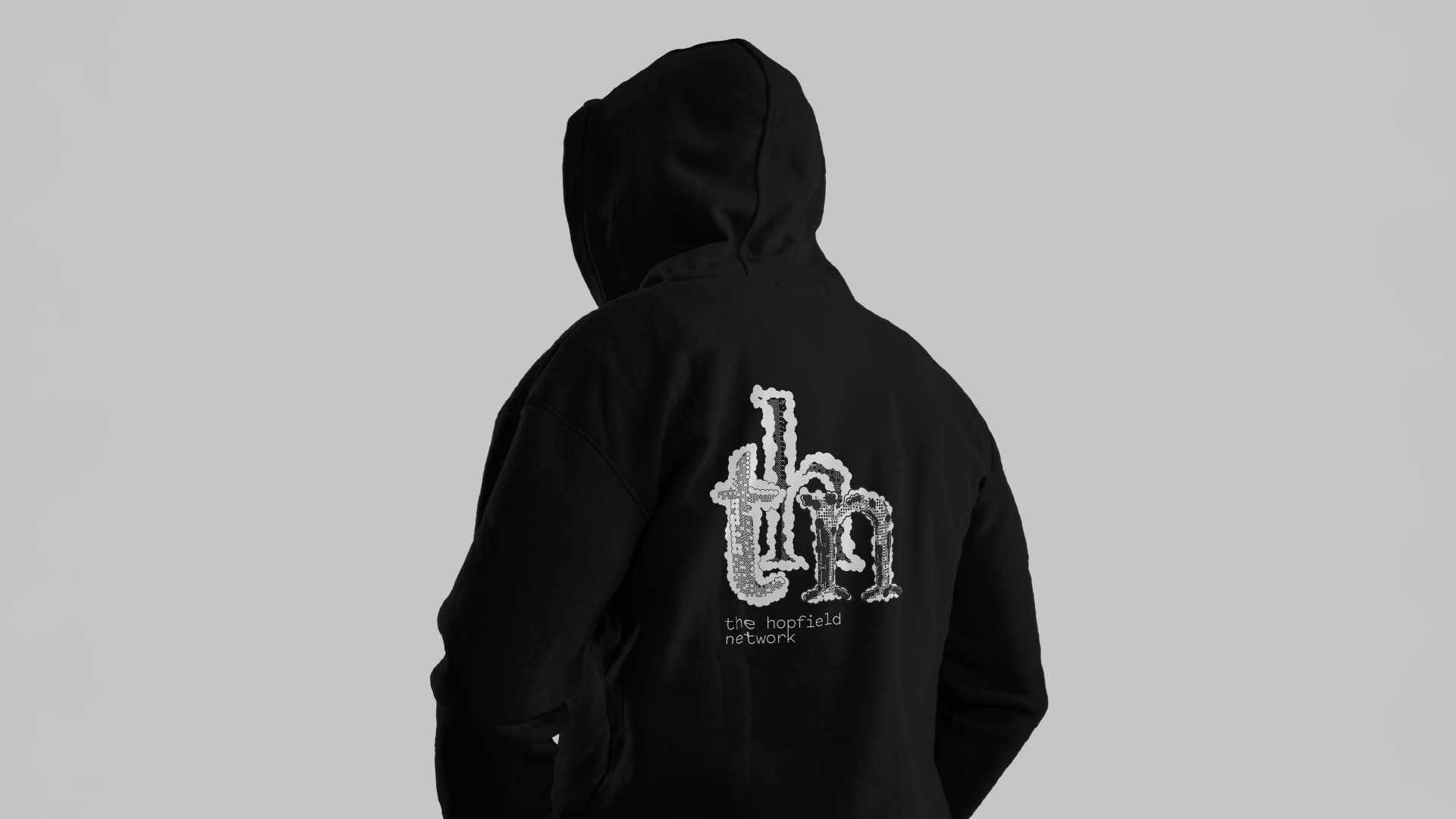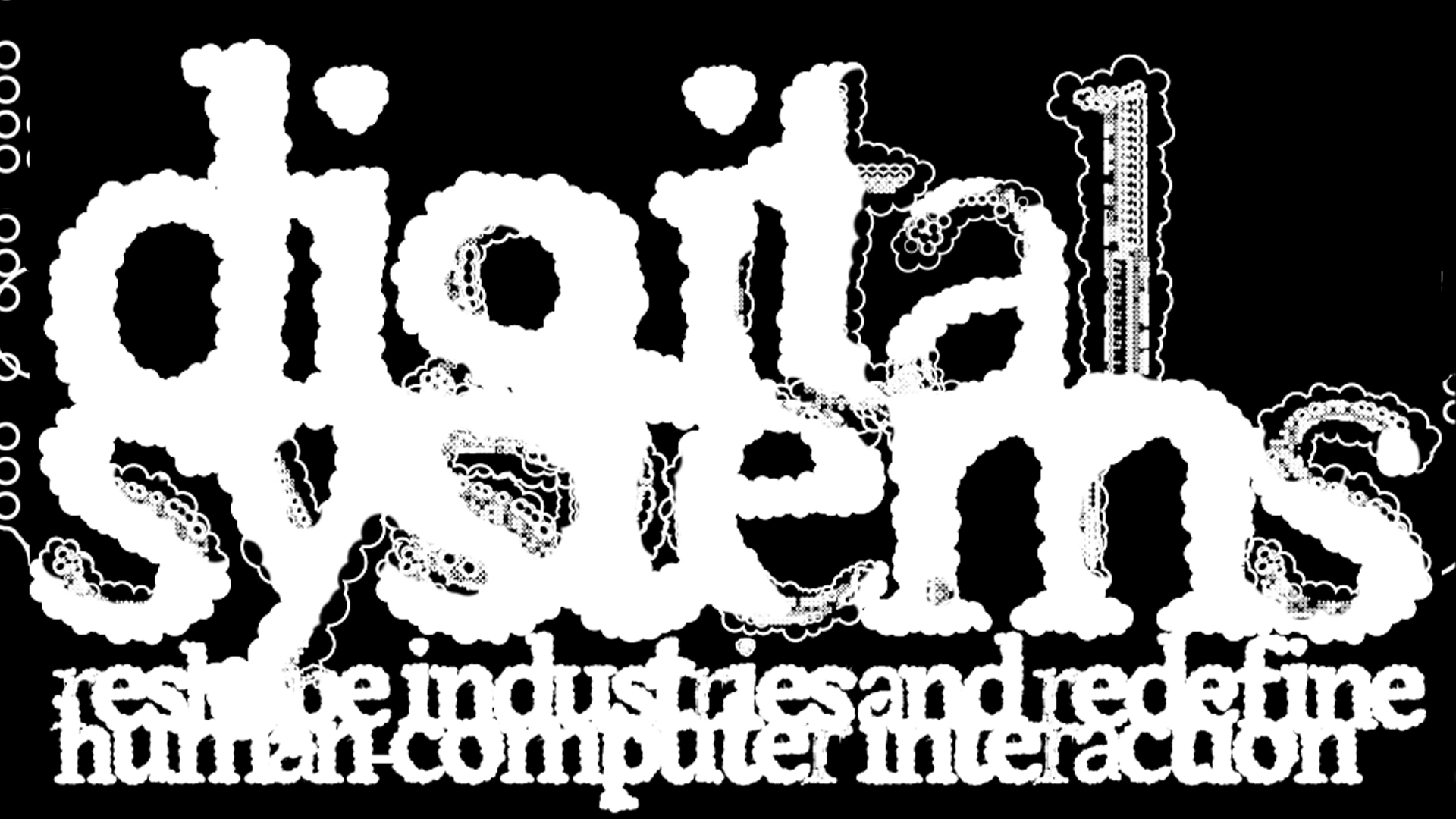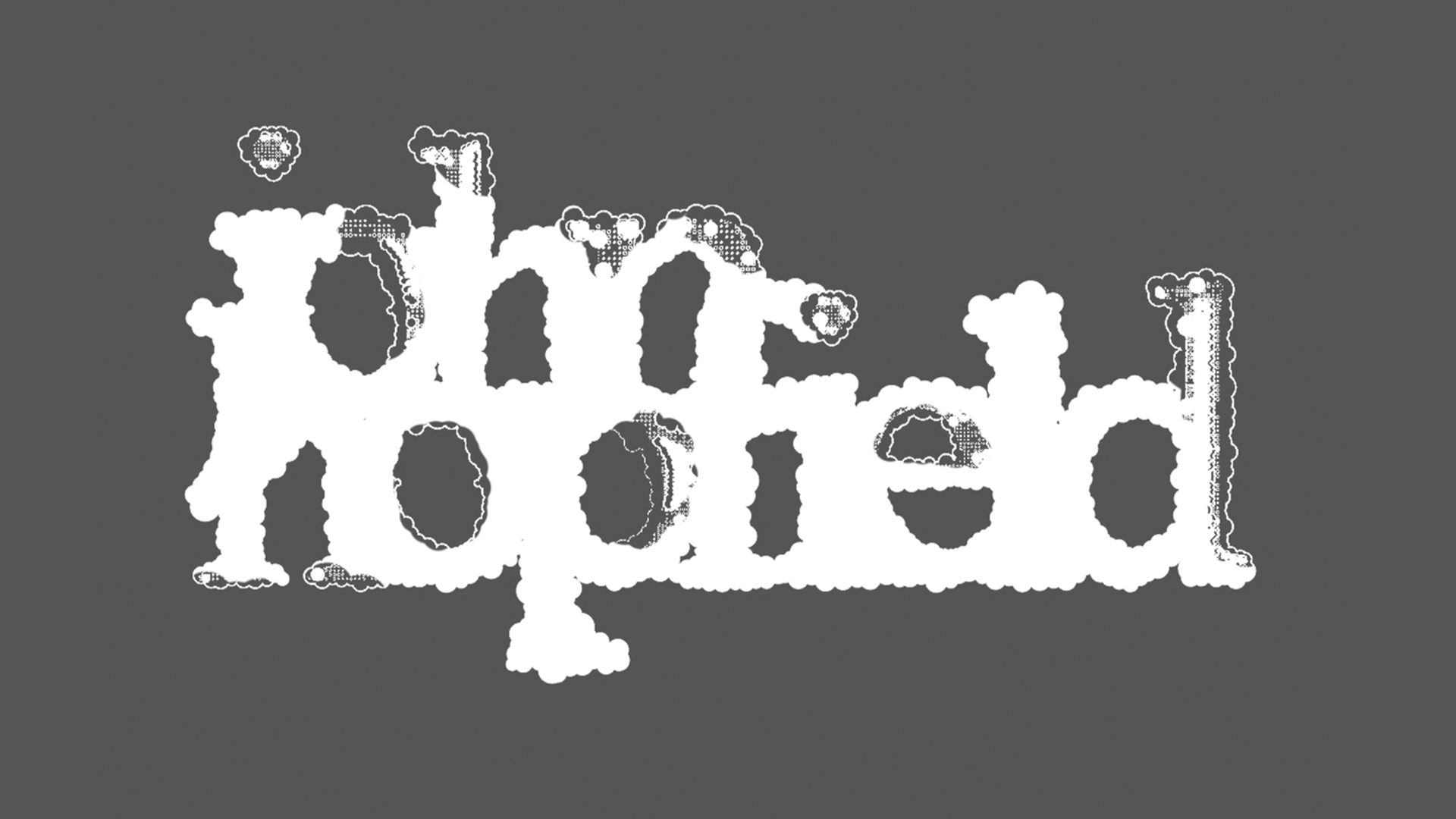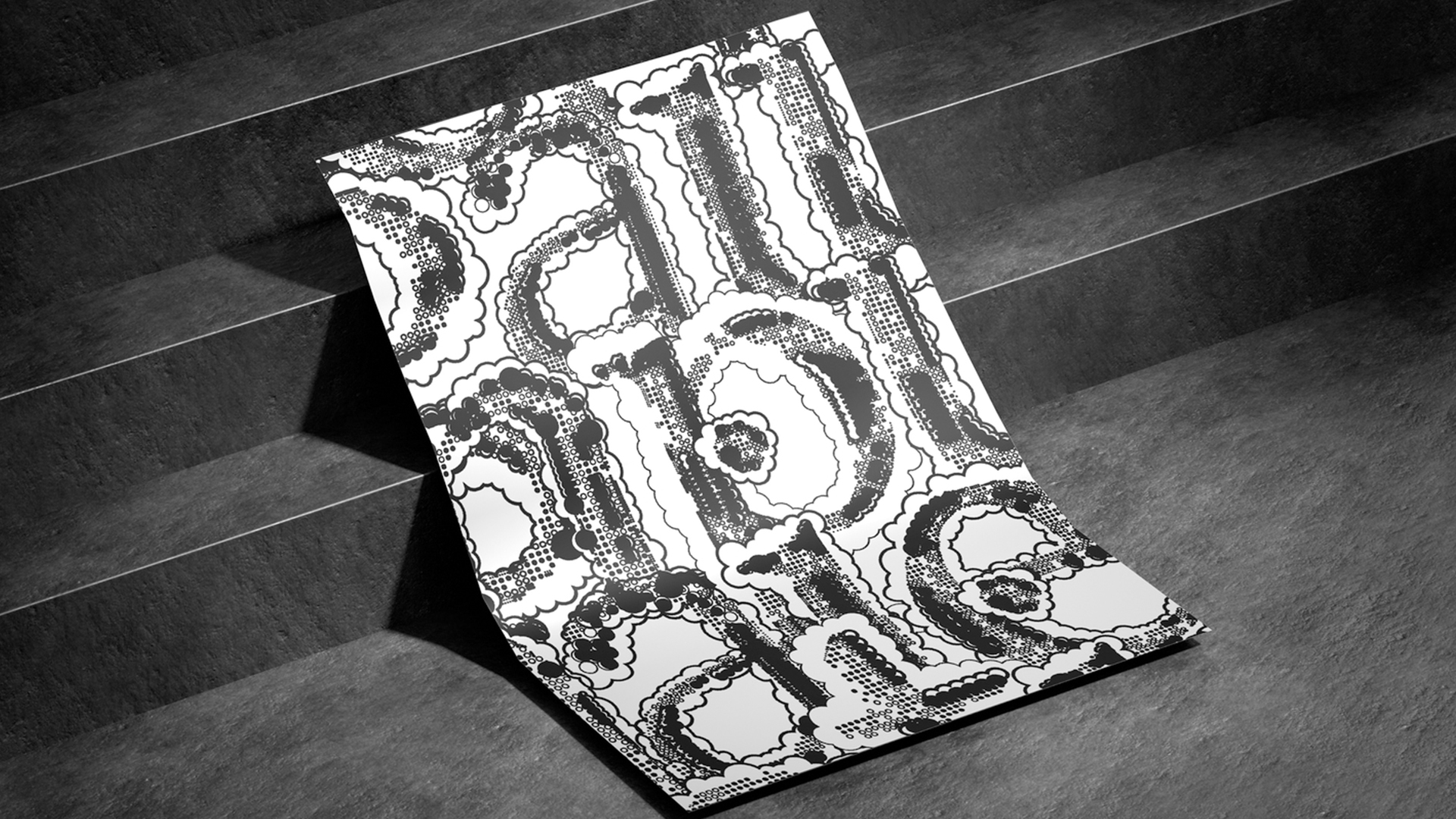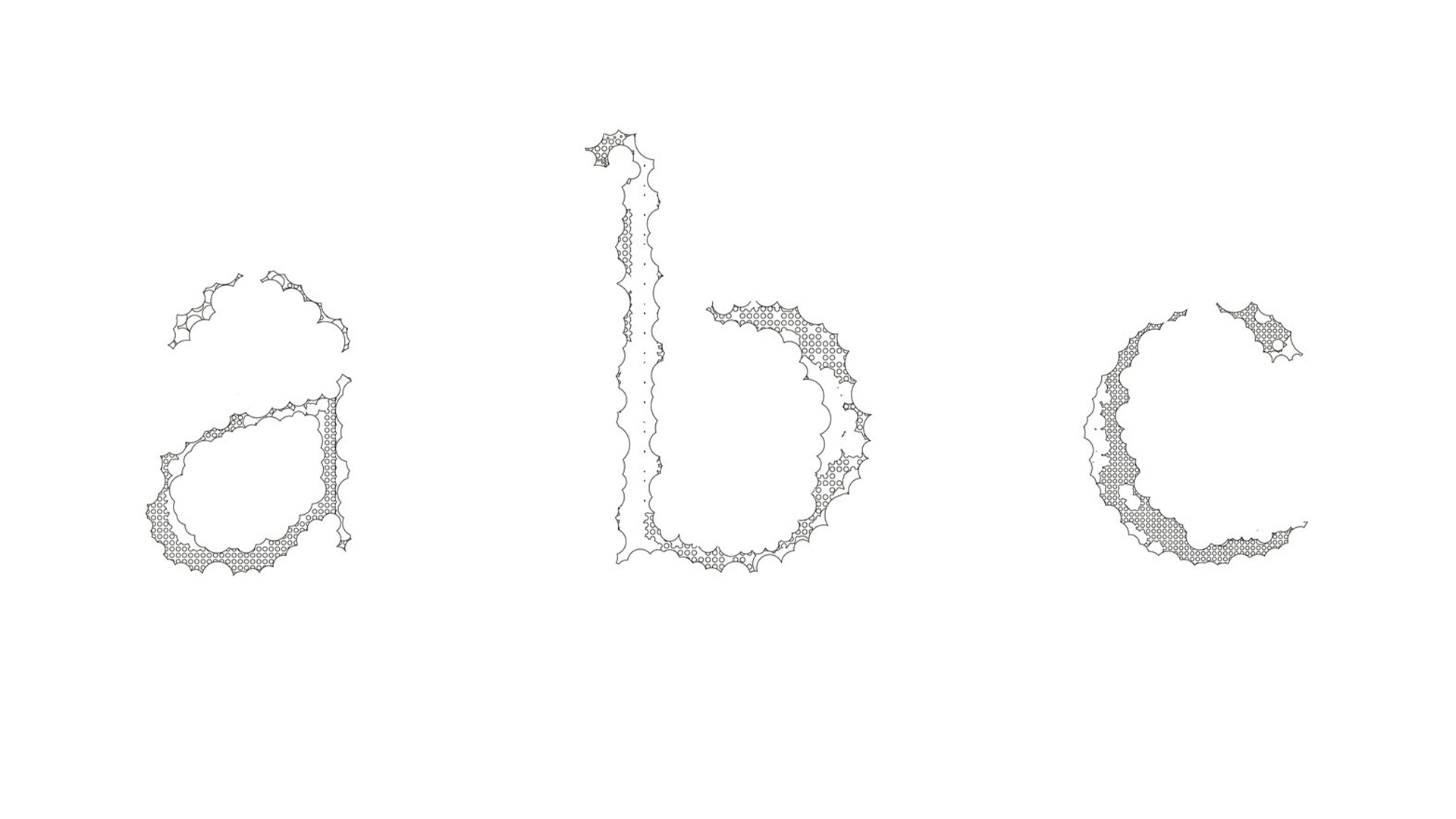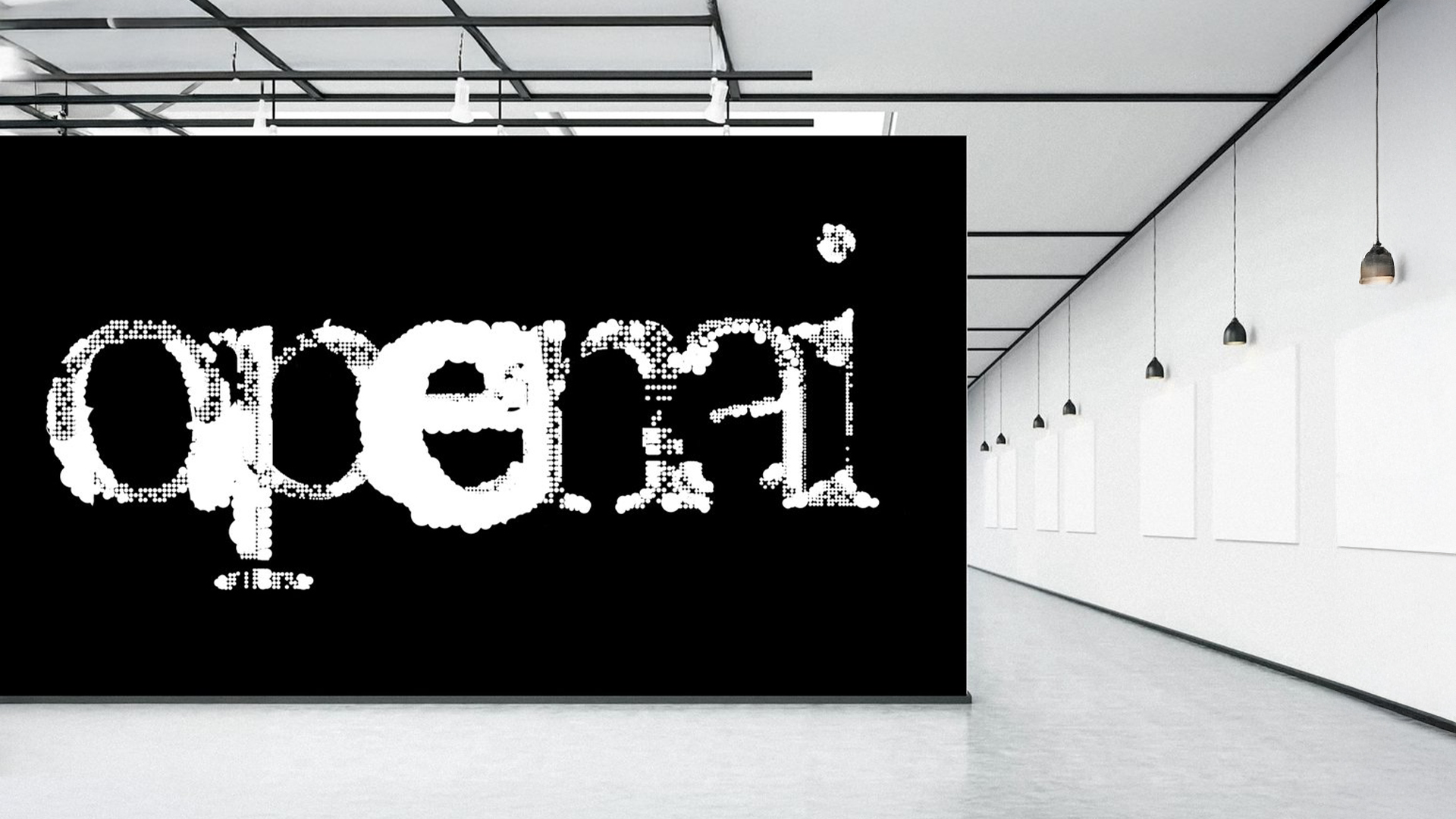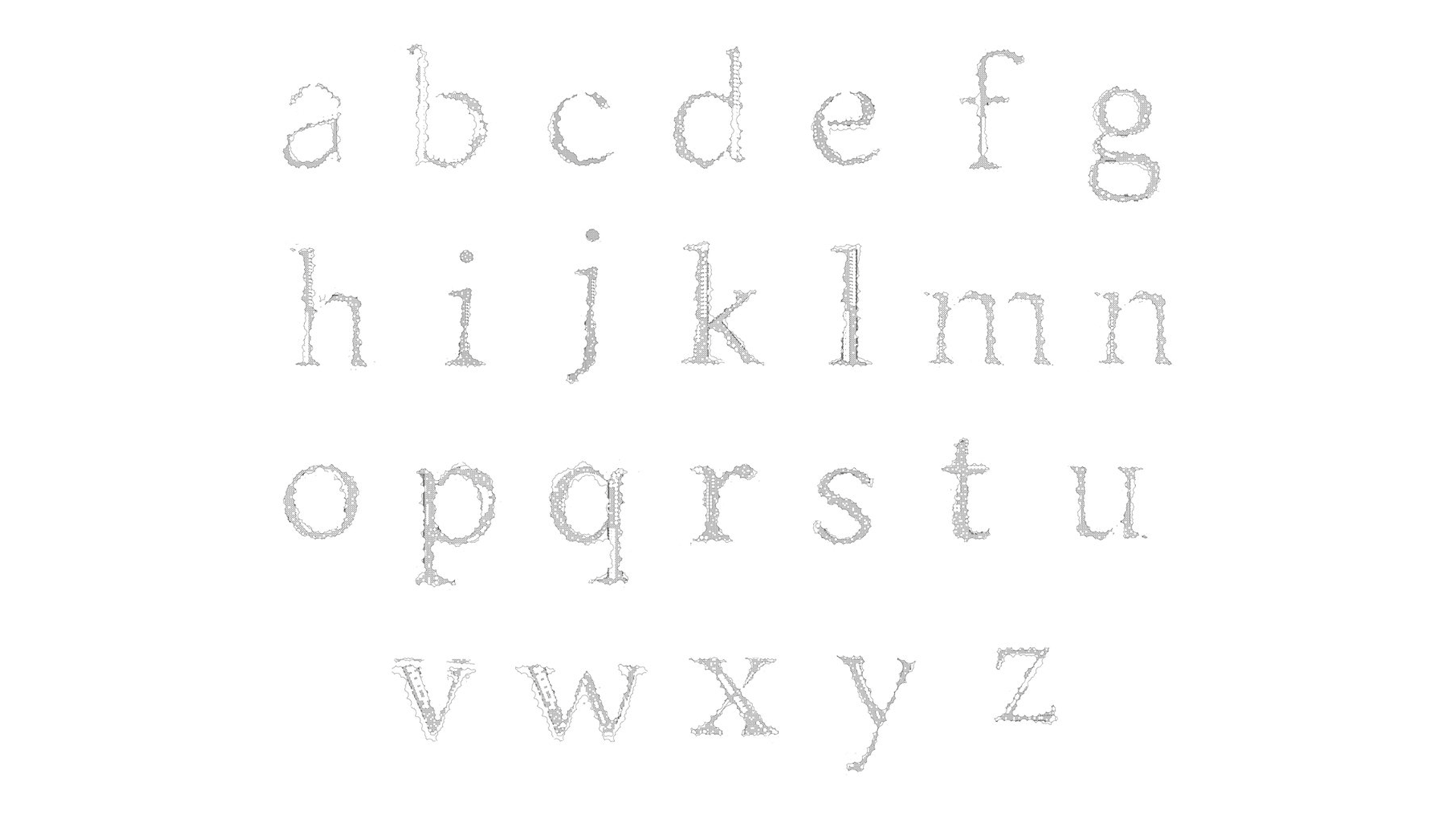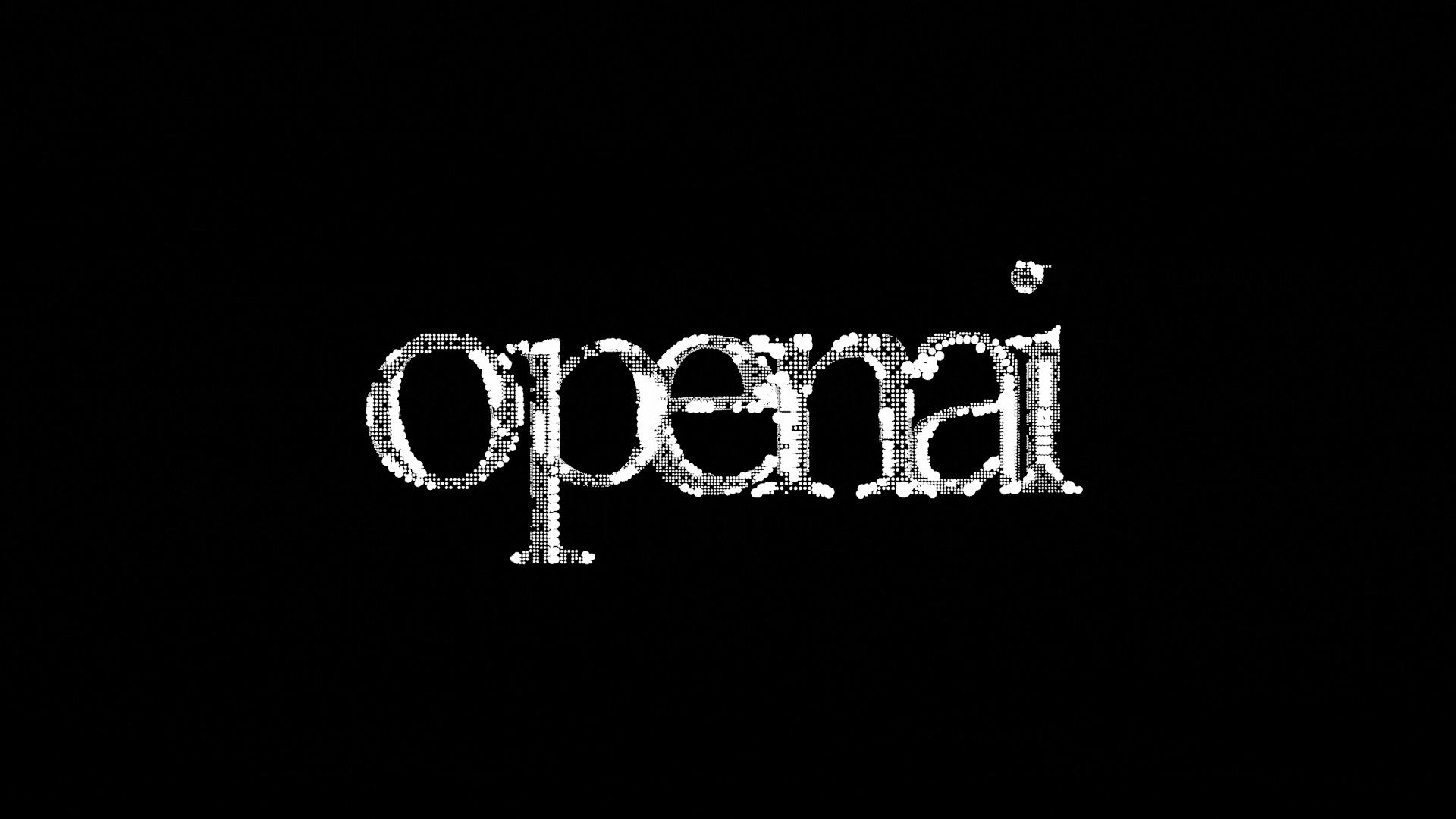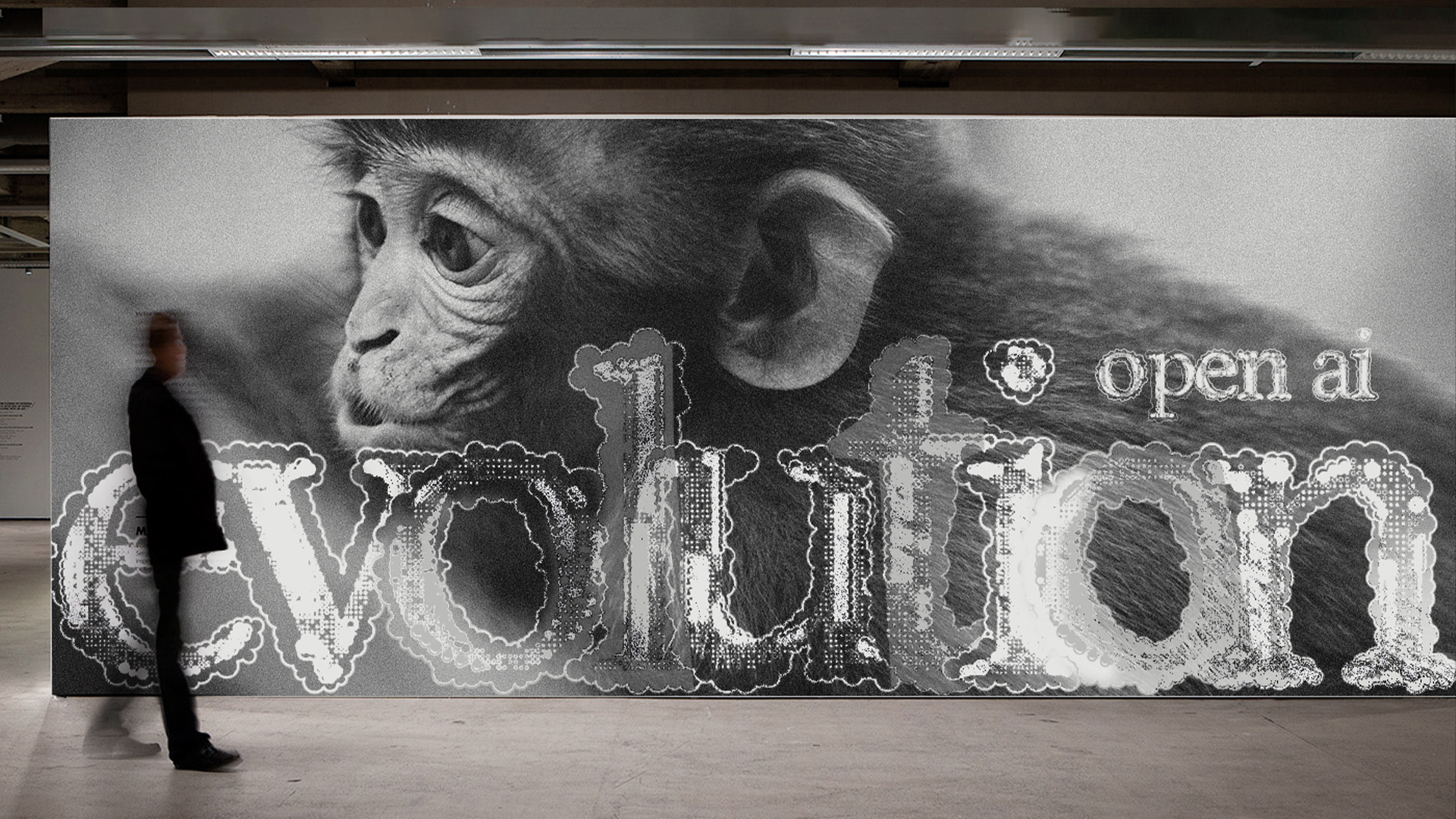
OAI THN Typeface
(OpenAI and The Hopfield Network Typeface)
Классическая сеть Хопфилда — это нейронная сеть и первая архитектура в ИИ, которая научилась работать как «ассоциативная память». Она хранит образы и восстанавливает их даже из неполных данных. Хопфилд послужил идейным вдохновителем последующих исследований в области ИИ, а в дальнейшем создании всеми нами известного OpenAI.
Требования к шрифту: самообучающийся, инновационный, умный, адаптивный, аналитический, виртуальный, гибкий, технологичный.
Чтобы воссоздать самовоспроизводящийся шрифт, в проекте была построена сеть на 128×128 ячеек. В данную сеть через метод загрузки ранее известных антикв и в меньшем количестве гротесков сформировался уникальный шрифт. Первый слайд как раз демонстрирует четыре итерации шрифта.
Важная составляющая — энергетическая функция (Lyapunov функция), которая убывает при переходах состояния, и сеть постепенно “спускается” к локальному минимуму энергии. На третьем слайде этот эффект наглядно продемонстрирован.
Айдентика стала для меня способом перевести сложную математику и алгоритмы в визуальный язык. Данный шрифт это моя дизайнерская интерпретация образа сетей Хопфилда и OpenAI, где я пытаюсь донести главные свойства ИИ: интеллект, точность, адаптивность и технологичность.
Шрифт выступает медиатором между абстрактной наукой и человеческим восприятием.